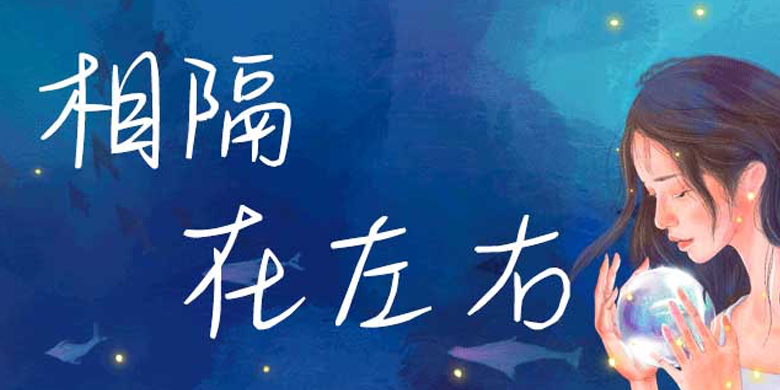
方正手迹-相隔在左右
方正手迹-相隔在左右,这款字体结构工整、笔画清晰,兼顾美观与易读性,适用于标题、正文、海报、包装、LOGO 等多种场景。字形优雅稳定,风格百搭耐看,适配日常排版与创意设计,让文字呈现更舒适、更具质感。方正手迹-相隔在左右一笔一画,皆是细节,以均衡的比例、流畅的线条打造舒适视觉体验,字形端正大气,风格简约现代。无论是商业设计、品牌宣传还是日常排版,都能轻松驾驭,让文字更有格调与力量。方正手迹-相隔在左右字体下载。
相隔在左右这款字体线条简洁明了,字形简单大方。转折多做圆弧处理,笔意连贯别有风味。适用于文艺类的书刊、品牌广告和产品包装设计,以及社交网络的个性化用字。